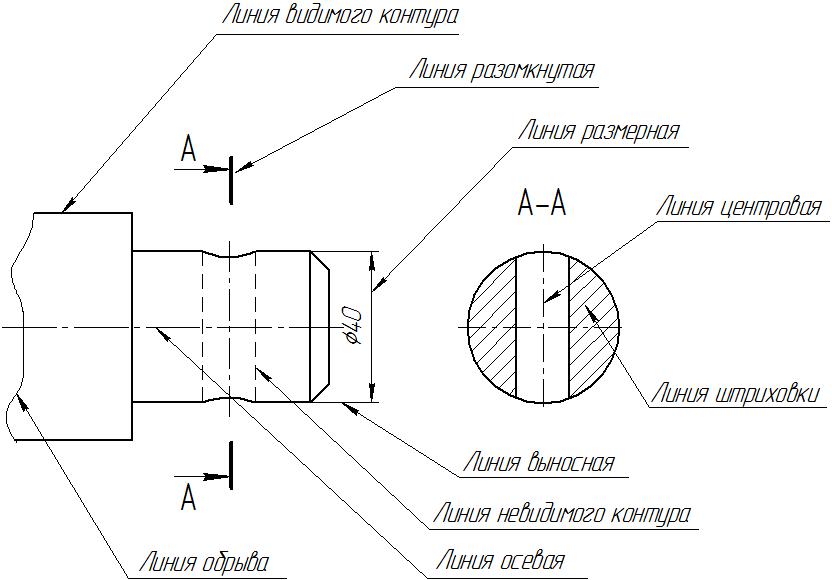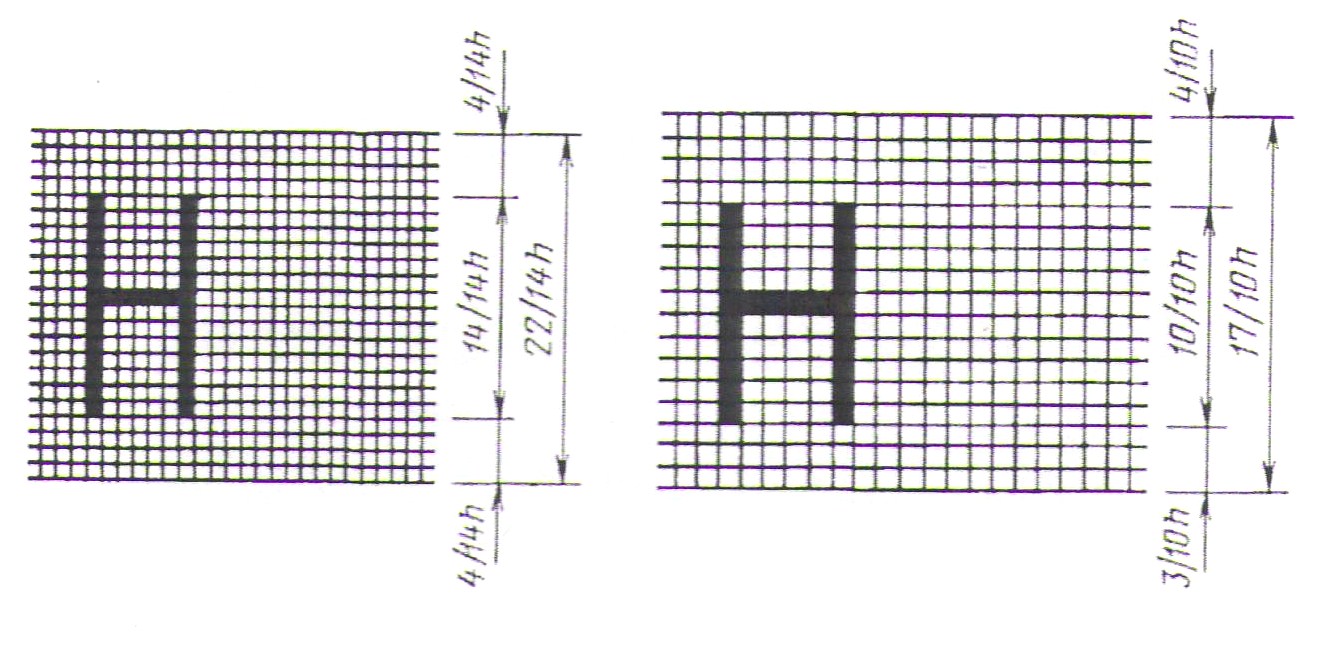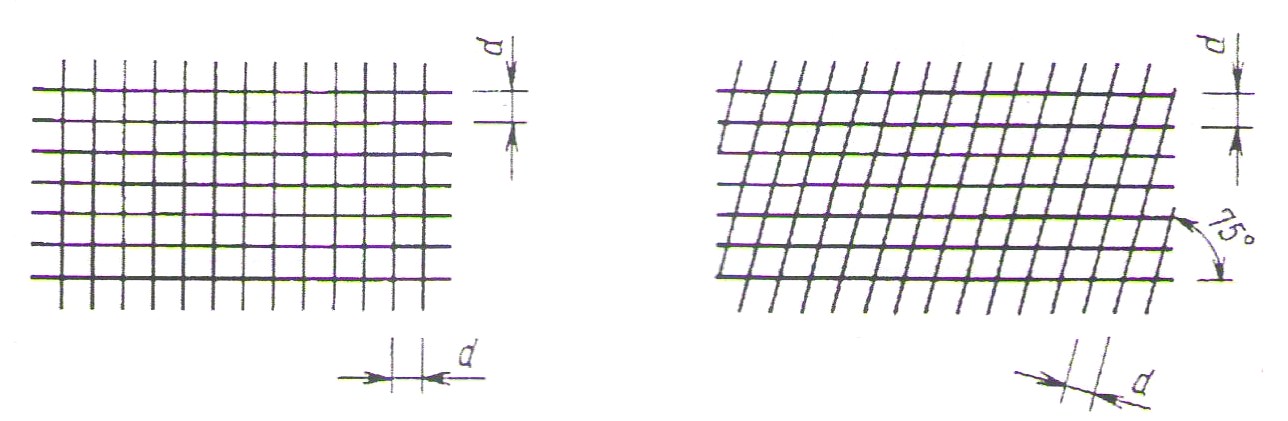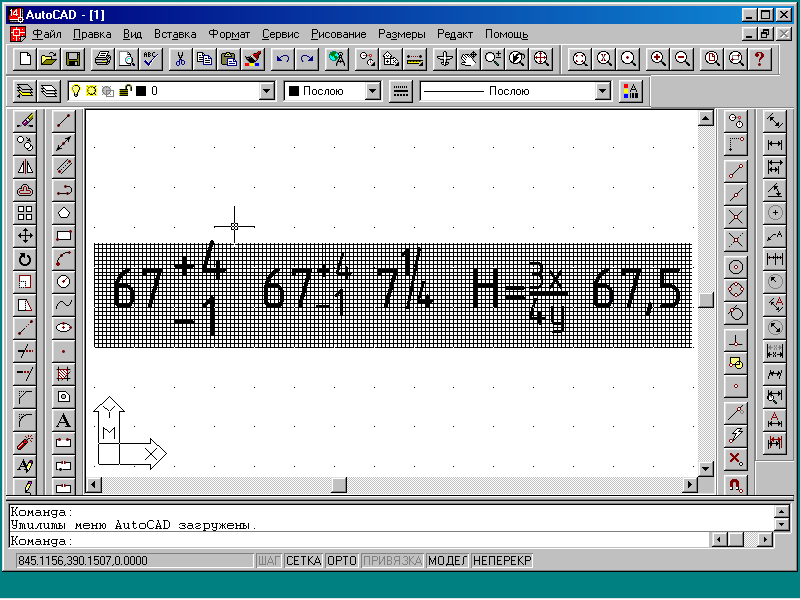
Шрифты чертежные
Линии Масштабы. Все чертежи выполняют в масштабах, утвержденных ГОСТ 2.302-68. Масштабы изображений в чертежах в зависимости от сложности и величины изображаемых изделий или их составных частей, а также от вида чертежа нужно выбирать из представленного в табл.1.3 ряда. Таблица 1.3
Масштаб, указанный в предназначенной для этого графе основной надписи чертежа, должен обозначаться по типу 1:1; 1:2; 2:1 и т. д. Масштаб изображения, отличающийся от указанного в основной надписи, помещают справа от надписи, относящейся к изображению. Например:
A (1:2), А-А (1:2).
Все чертежи выполняют линиями различного типа и толщины, причем толщина линий зависит от величины, сложности и назначения чертежа. ГОСТ 2.303-68 устанавливает начертания и основные назначения линий на чертежах (рис. 1.4). Указанный стандарт устанавливает назначение и начертание девяти типов линий, это – сплошная (основная, тонкая, волнистая и тонкая с изломами), штриховая, штрихпунктирная (тонкая, утолщенная и с двумя точками) и разомкнутая линии (табл. 1.4).
Рис. 1.4
Сплошная основная линия применяется для изображения видимого контура предмета, линий пересечения одной поверхности с другой и контура сечения (вынесенного или входящего в состав разреза). Толщину сплошных основных линий следует выбирать от 0,5 до 1,4 мм в зависимости от размеров и сложности изображения, а также от формата чертежа. Выбранная толщина линии должна быть одинакова для всех изображений на данном чертеже, вычерчиваемых в одинаковом масштабе. Сплошная тонкая линия предназначена для построения, выносных и размерных линий, штриховки разрезов и сечений, линии контура наложенного сечения, линии-выноски, полки линий выносок и подчеркивание надписей и др., (см. табл. 1.3). Расстояние между линиями штриховки принимают от 1 до 10 мм в зависимости от величины площади штриховки. Волнистой линией показывают линии обрыва и линии разграничения вида и разреза.
Таблица 1.4
Окончание табл. 1.4
. Наименьшая толщина линий и наименьшее расстояние между линиями в зависимости от формата чертежа должны соответствовать указанным в табл. 2. Таблица 2
Штриховую линию применяют для изображения на чертежах линий невидимого контура. Характерная особенность этой линии состоит в том, что ее толщина выбирается в том же интервале, что и 2, 3, 5,8 и 9 (табл. 4), но она должна быть чуть толще их. Это делается для того, чтобы показать, что эта линия находится на контуре и существует, в отличие от 2, 3, 5,8 и 9 линий, которые существуют виртуально, и на самой детали их нет. Штрихпунктирной тонкой линией проводят осевые штрих-пунктирная линия, изображающая на чертеже ось предмета или его поверхности и центровые линии штрихпунктирная линия, проходящая через центры поверхностей вращения или через геометрический центр и центр тяжести (РИС.1.11, б), линии сечений, являющиеся осями симметрии для наложенных или вынесенных сечений. Штрихпунктирная тонкая линия с двумя точками применяется для изображения линий сгиба и частей изделий в крайних или промежуточных положениях, а также для изображения развертки, совмещенной с видом. Утолщенная штрихпунктирная линия применяется для обозначения поверхности, подлежащей термической обработке или нанесения покрытия. Размеры штрихов линий даны в таблице 4. Штрихи в линии должны быть приблизительно одинаковой длины. Штрихпунктирные линии должны заканчиваться штрихами, которые рекомендуется выводить за контур изображения предмета на 3 Разомкнутую линию применяют для обозначения линий разрезов и сечений (см. рис. 1.4, А–А).Ее толщина должна быть толще контурной, примерно в полтора раза, что позволяет с легкостью находить штрихи, особенно когда они находятся внутри изображений (штрихи ломаных и ступенчатых разрезов). Длину штрихов в этих линиях следует выбирать в пределах от 8 до 20 ммв зависимости от величины изображения. Нарушения при нанесении линий приводит увеличению времени на чтение чертежа рабочим и может быть причиной брака при изготовлении детали, изделия, что в конечном итоге приведет к неоправданным производственным издержкам.
ГОСТ 2.304-81 регламентирует правила написания шрифтов (букв, цифр, условных знаков). Необходимость строгого соблюдения этого ГОСТа продиктована проблемой быстрого и безошибочного распознавания надписей невооруженным глазом или вооруженным, или «читающим» устройством в различных условиях (при различной освещенности, когда наблюдатель неподвижен, а движется чертеж или наоборот). Кроме того, чертежи со временем могут изнашиваться и надписи становятся менее четкими. Ошибки при чтении размерных чисел недопустимы. Поэтому к качеству шрифта на чертежах предъявляют особые требования. В соответствий с требованиямиГОСТ 2.304-81 шрифты, применяемые при оформлении чертежей и других технических документов всех отраслей промышленности и строительства, выполняют с наклоном под углом 75о к основанию строки (рис. 1.5) или без наклона (рис. 1.6). Кроме того, устанавливается два типа шрифта (рис.1.7): тип А с толщиной линии 1:14 (табл.1.5) и тип Б с толщиной 1:10 (табл. 1.6).
Таблица 1.5 Основные параметры шрифта типа А
Таблица 1.6 Основные параметры шрифта типа Б
Рис. 1.7
Стандарт предусматривает следующие термины, обозначения и определения (рис. 1.8): 1. Размер шрифта h ‑ величина, определенная высотой прописных букв в миллиметрах. 2. Высота прописных букв h измеряется перпендикулярно к основанию строки. Высота строчных букв с определяется из отношения их высоты (без отростков k) к размеру шрифта h, например c =7/10 h.
3. Ширина буквы g определяется в соответствии с приложениями к таб. 1.5 и 1.6. 4. Толщина линии шрифта d, расстояние между буквами а и минимальное расстояние между строками b определяются в зависимости от типа шрифта (см. табл. 1.5 и 1.6). При выполнении надписей шрифтом вначале необходимо построить карандашом сетку (рис.1.9) в виде тонких линий, а затем от руки нанести на эту сетку буквы и цифры тонкими линиями. Необходимая толщина линий букв и цифр достигается при обводке мягким карандашом.
Рис.1.9
Применение шрифта размера, меньшего чем 3,5, при нанесении размерных чисел на чертежах, выполненных в карандаше, не допускается. Дроби, показатели, индексы и предельные отклонения выполняют шрифтом на одну ступень меньшим, чем размер шрифта основной величины, или одинакового размера с ним (рис. 1.10). Следует десятичные знаки отделять четко выполненной запятой (в виде черты), оставляя для нее достаточный промежуток между смежными цифрами.
Рис. 1.10 В заключении отметим, что не соблюдение стандарта 2.304-81 приводит к неправильному прочтению текста, что вызывает брак при изготовлению изделия и в конечном итоге – удорожанию продукции. То же самое произойдет при сканировании, когда неправильно написанный текст не читается компьютером. В данном случае необходимо приглашать корректировщика, что опять увеличивает себестоимость продукции.